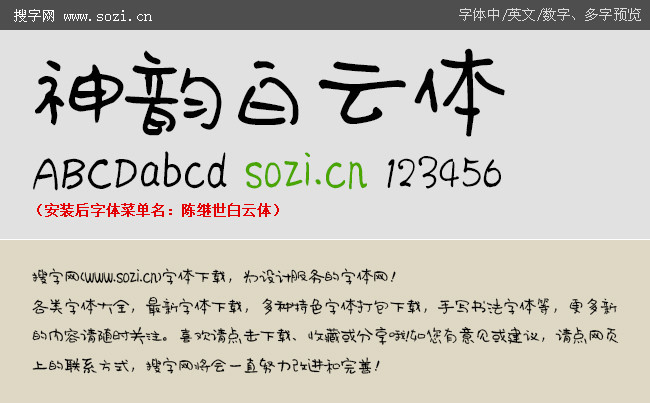
神韻白云體
搜字網(wǎng)給大家提供一款神韻白云體中文字體下載,神韻白云體是一款十分精致美觀的字體,字體可愛有趣,整體效果非常出色,適合應(yīng)用于平面海報設(shè)計、包裝設(shè)計等廣告應(yīng)用。(本字體為個人非商用版,如需要商用請聯(lián)系作者購買版權(quán))